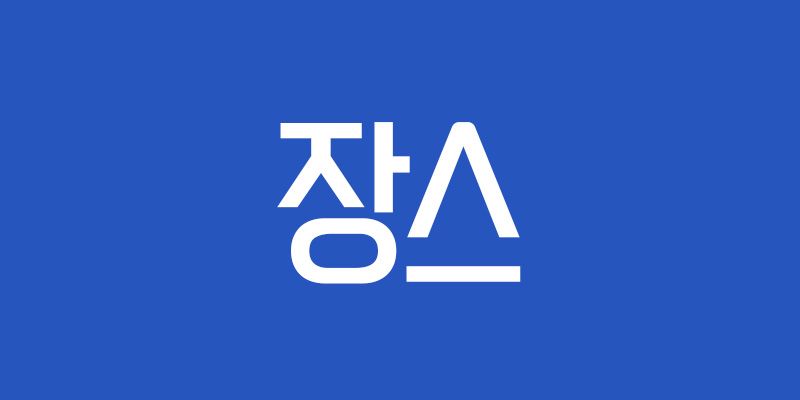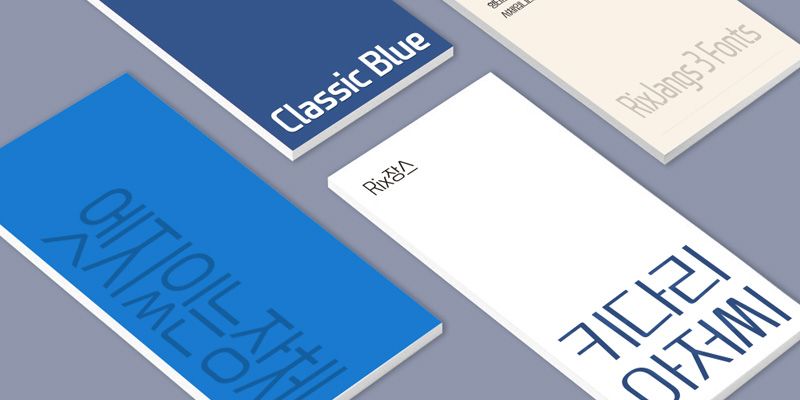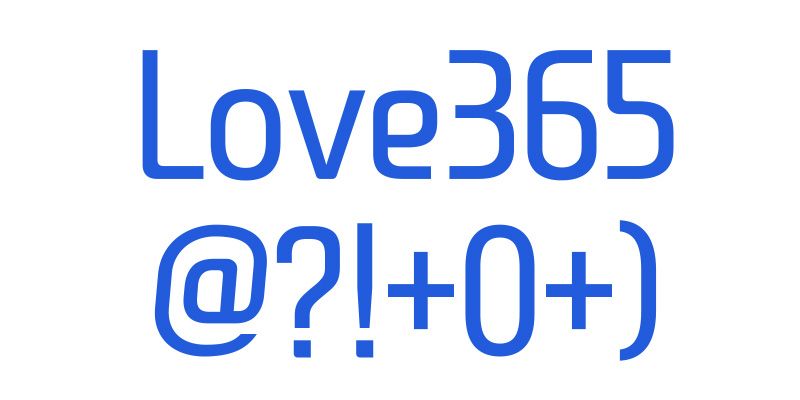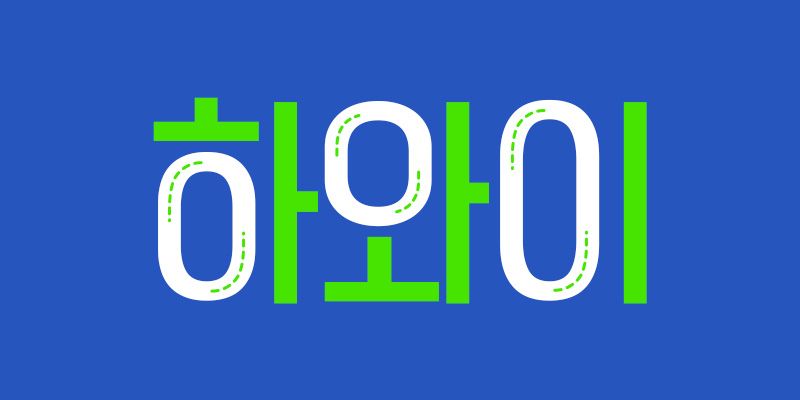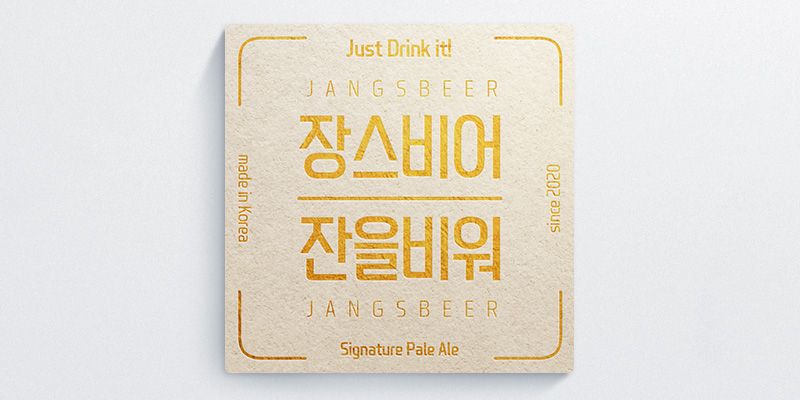
RixJangs ist eine Schrift, deren Entwicklungskonzept schmal, aber voller Module ist. Die einfachen geraden Linien werden mit weichen runden Häuten kombiniert. Sie wurde mit Variablen entworfen, die instabile Formen und Dicken, die durch schmalere Buchstabengrößen entstehen, ergänzen und so einen besseren Ausdruck der Zeichen erreichen. Diese Schrift eignet sich gut, um viele Zeichen in einem schmalen Raum auszufüllen oder um sie in einem gut sichtbaren Titel zu verwenden.